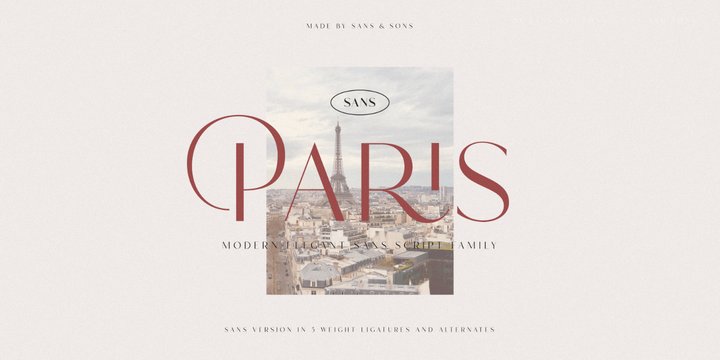
[Myfonts] Hello Paris Sans Font (2021)
Hello Paris Sans - современный санс с элегантным стилем.
Hello Paris Sans - это высококонтрастный шрифт, такой тонкий, разборчивый и подходящий для высококлассного брендинга, дизайна логотипов, упаковки продуктов, приглашений и мастер-бланков.